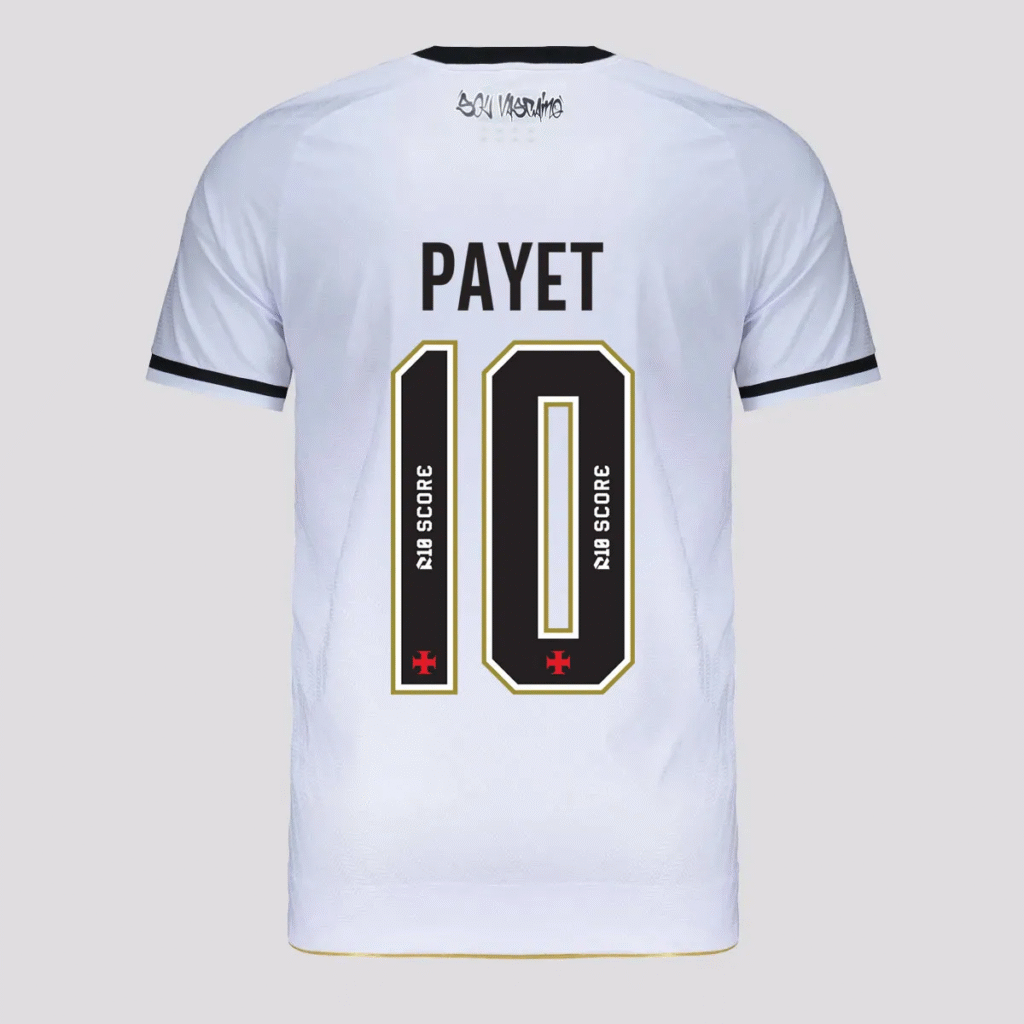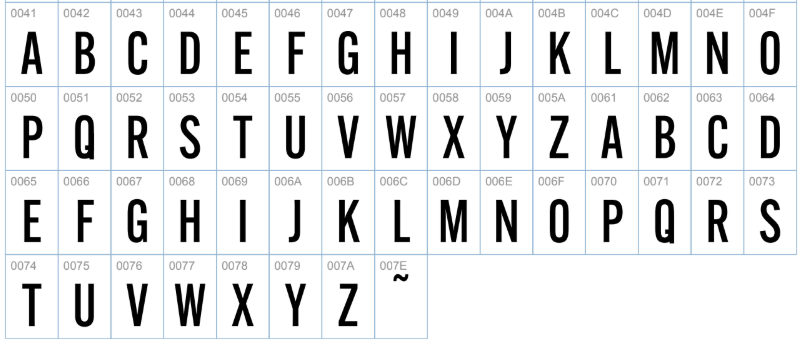
A paixão pelo Vasco da Gama é algo que o torcedor carrega no peito, e a camisa é o manto sagrado que representa essa devoção. Para a temporada 2025, a Kappa, fornecedora de material esportivo do clube, desenvolveu uma identidade visual renovada, e a tipografia (fonte) usada nos nomes e números é uma parte crucial desse design.
Seja você um designer gráfico, um entusiasta de camisas de futebol ou um torcedor que adora criar artes personalizadas, ter a fonte correta é essencial. Esta é a fonte exata que você vê nas costas dos jogadores do Gigante da Colina em 2025, pronta para ser usada em seus projetos.
O Estilo da Fonte Vasco 2025
A tipografia criada pela Kappa para o Vasco da Gama em 2025 busca um equilíbrio entre a tradição do clube e a modernidade exigida pelo design esportivo atual. A fonte apresenta linhas robustas e um design limpo, com excelente legibilidade. Os cantos são ligeiramente chanfrados, conferindo um senso de dinamismo e força, sem perder a elegância. É uma fonte que se impõe, garantindo que o nome do jogador e o número sejam vistos com clareza e impacto no campo.